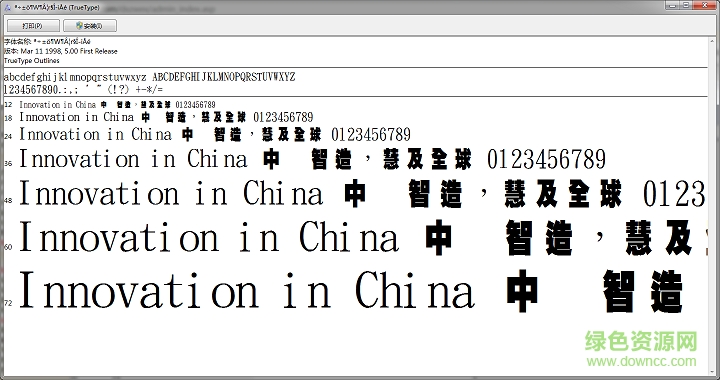
金梅超黑字形原體是一個(gè)黑體加粗類型的繁體字體,字體渾濁有力,大氣十足彰顯個(gè)性,喜歡的朋友快來綠色資源網(wǎng)下載吧!
金梅超黑字形原體是一款墨色稍重的美工藝術(shù)字體,該字體比較凝重大方,結(jié)構(gòu)也十分地流暢大方,整體上給人一種大氣、美觀和蒼勁有力的感覺,可以應(yīng)用于廣告設(shè)計(jì)、平面設(shè)計(jì)、印刷包裝、藝術(shù)繪畫等領(lǐng)域。